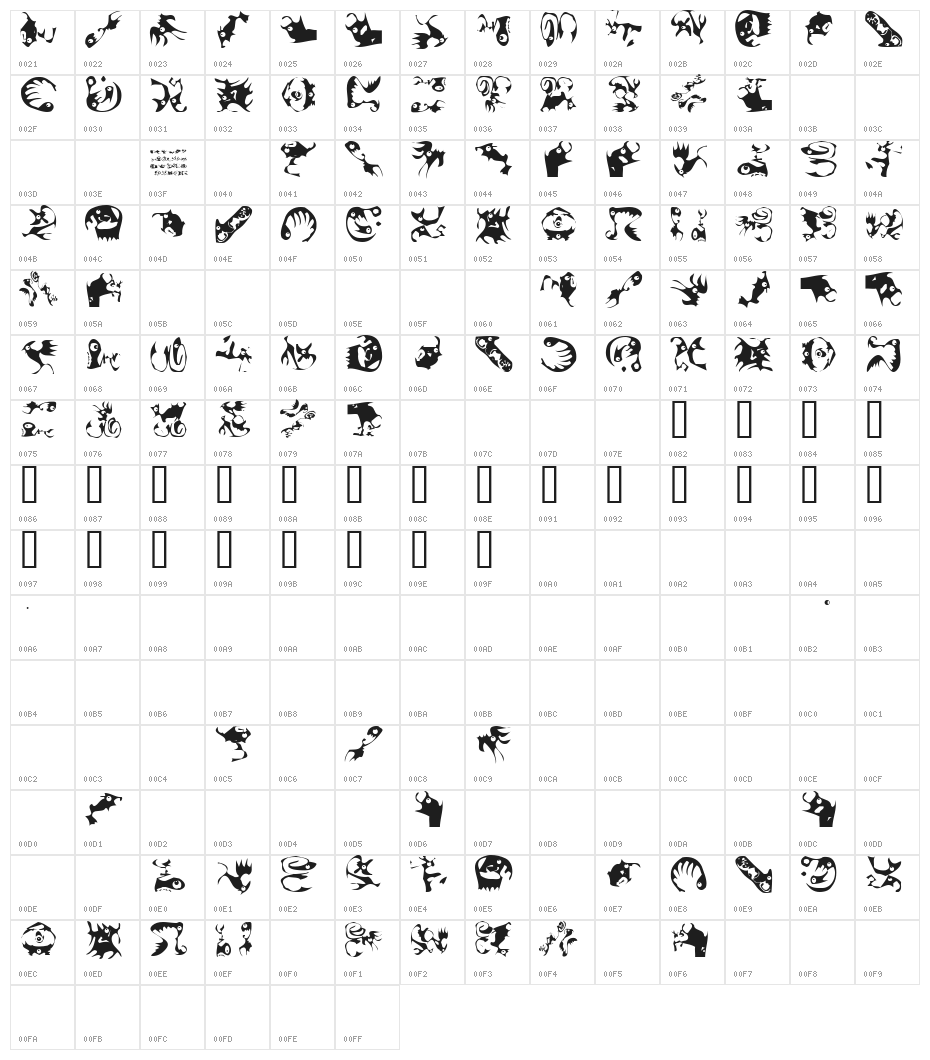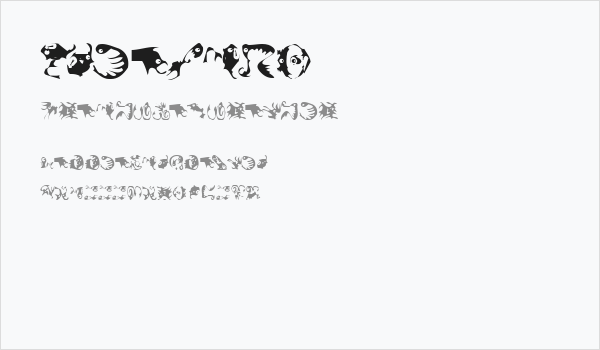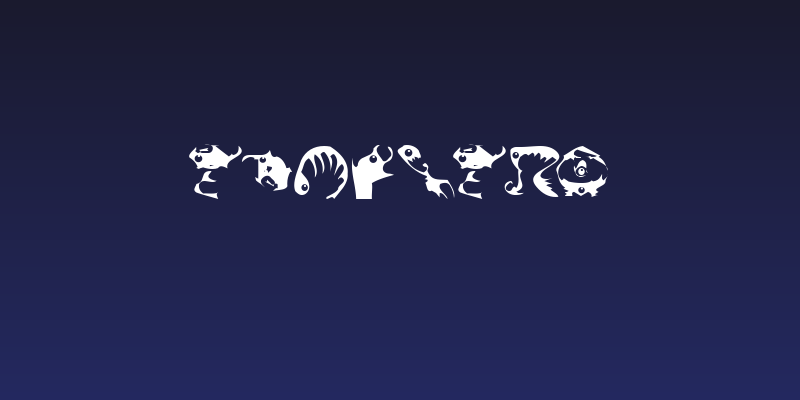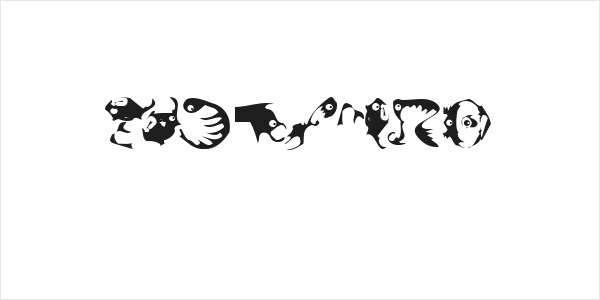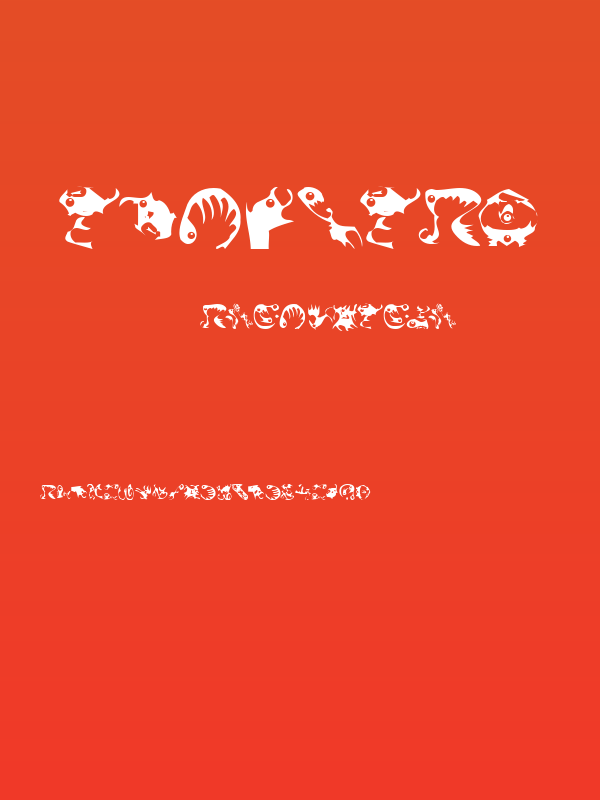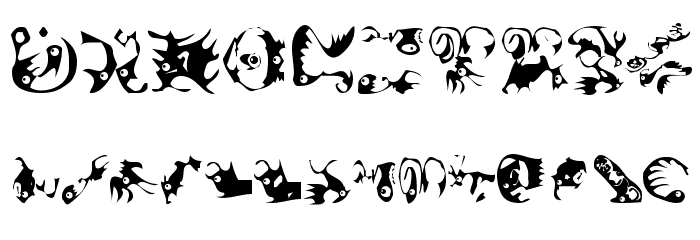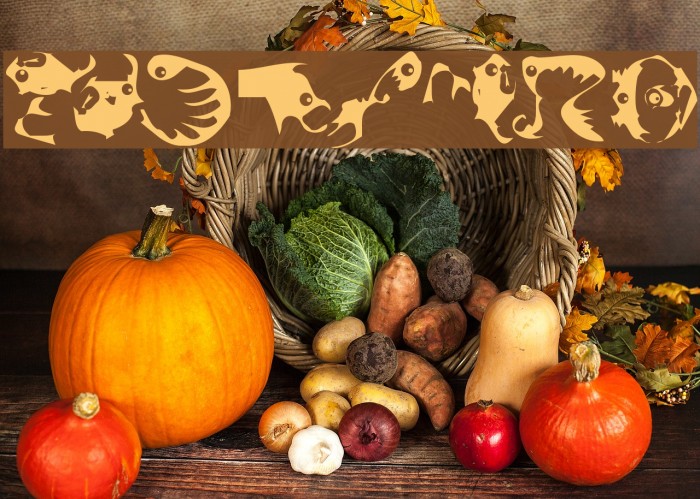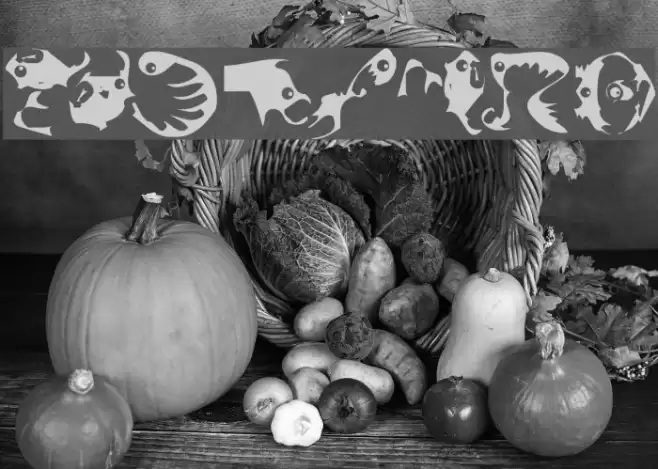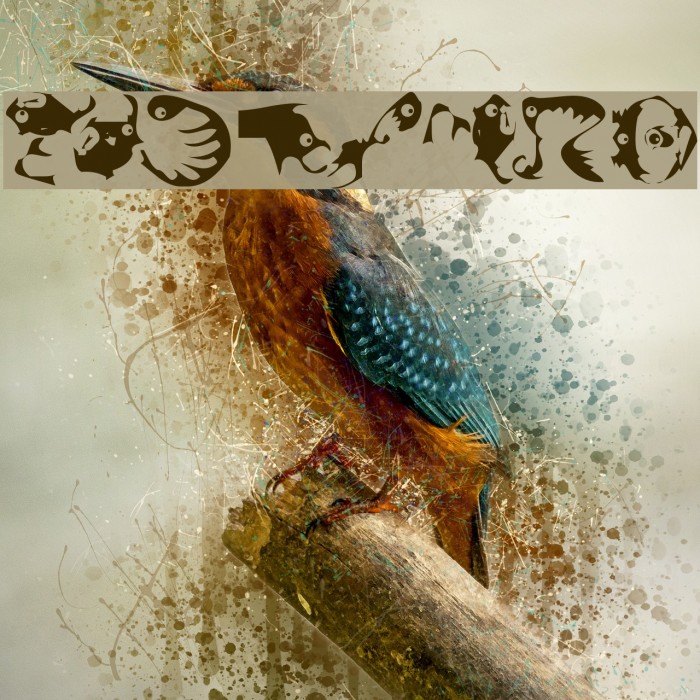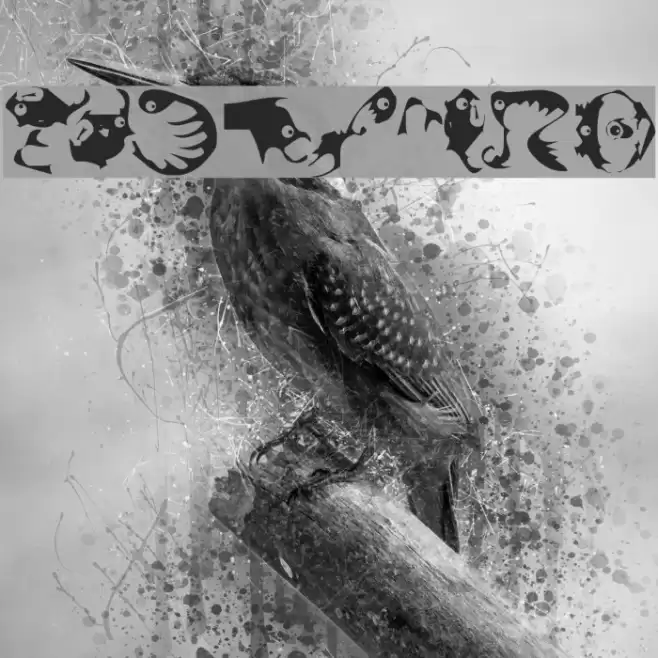
AmoebaTs Font
| Caz de utilizare | Logos, Posters, Artistic projects |
| Proiecte propuse | Ideal for artistic projects, children's book illustrations, creative posters, and unique branding materials. |